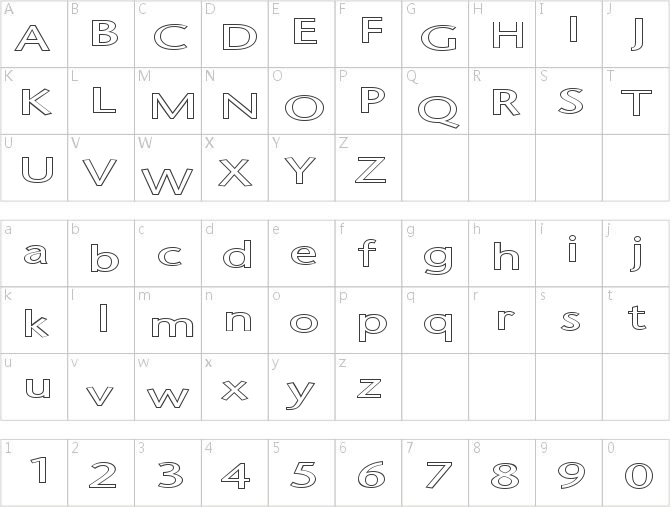
FZ BASIC 25 HOLLOW EX 詳情頁(yè)
FZ BASIC 25 HOLLOW EX字體字庫(kù)是一款讓人賞心悅目、百看不厭的英文字體,適合各類廣告和產(chǎn)品包裝設(shè)計(jì)應(yīng)用,字體大小0.07MB,格式為ttf字體,上傳用戶是曾紹文,作者/版權(quán)方為未知